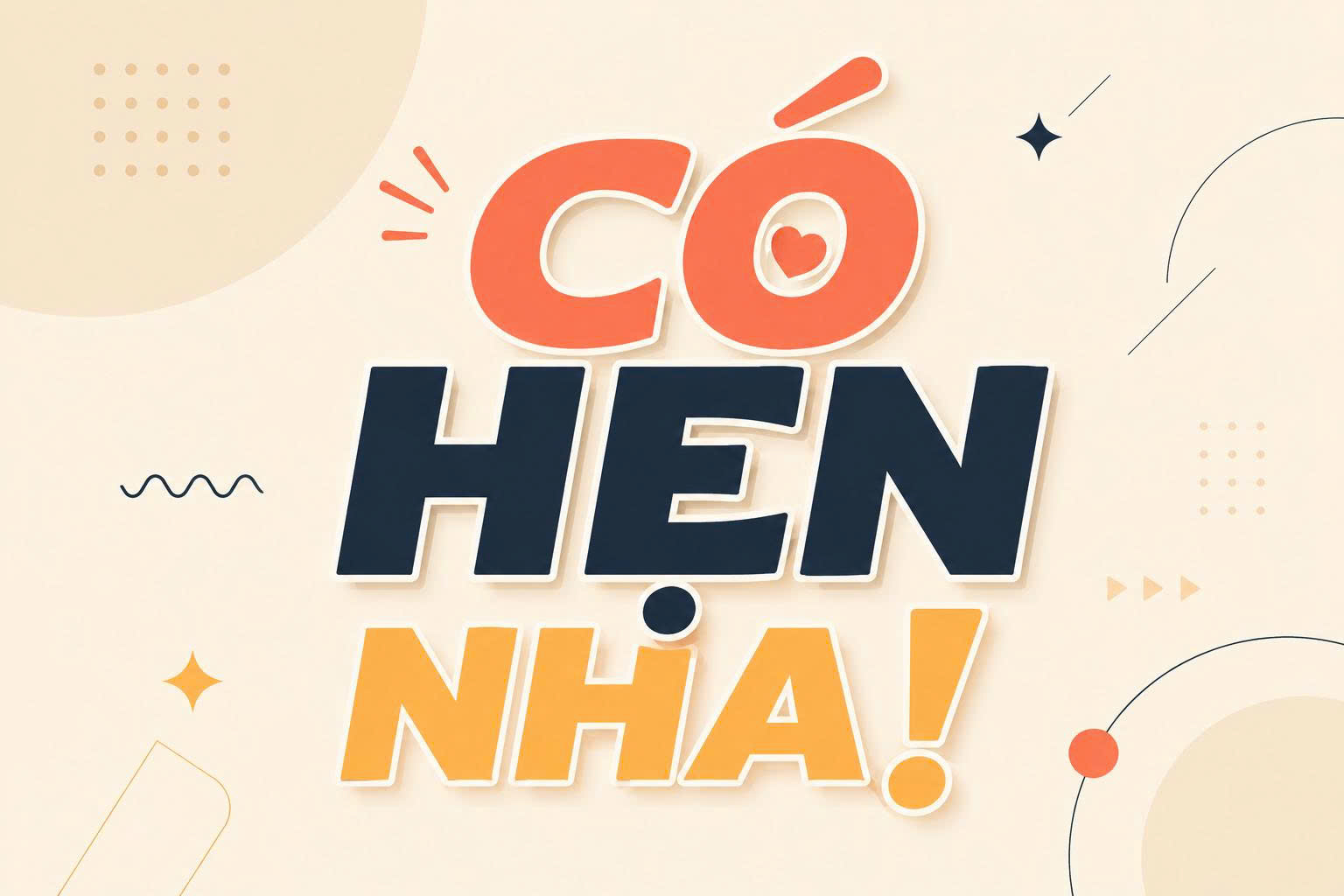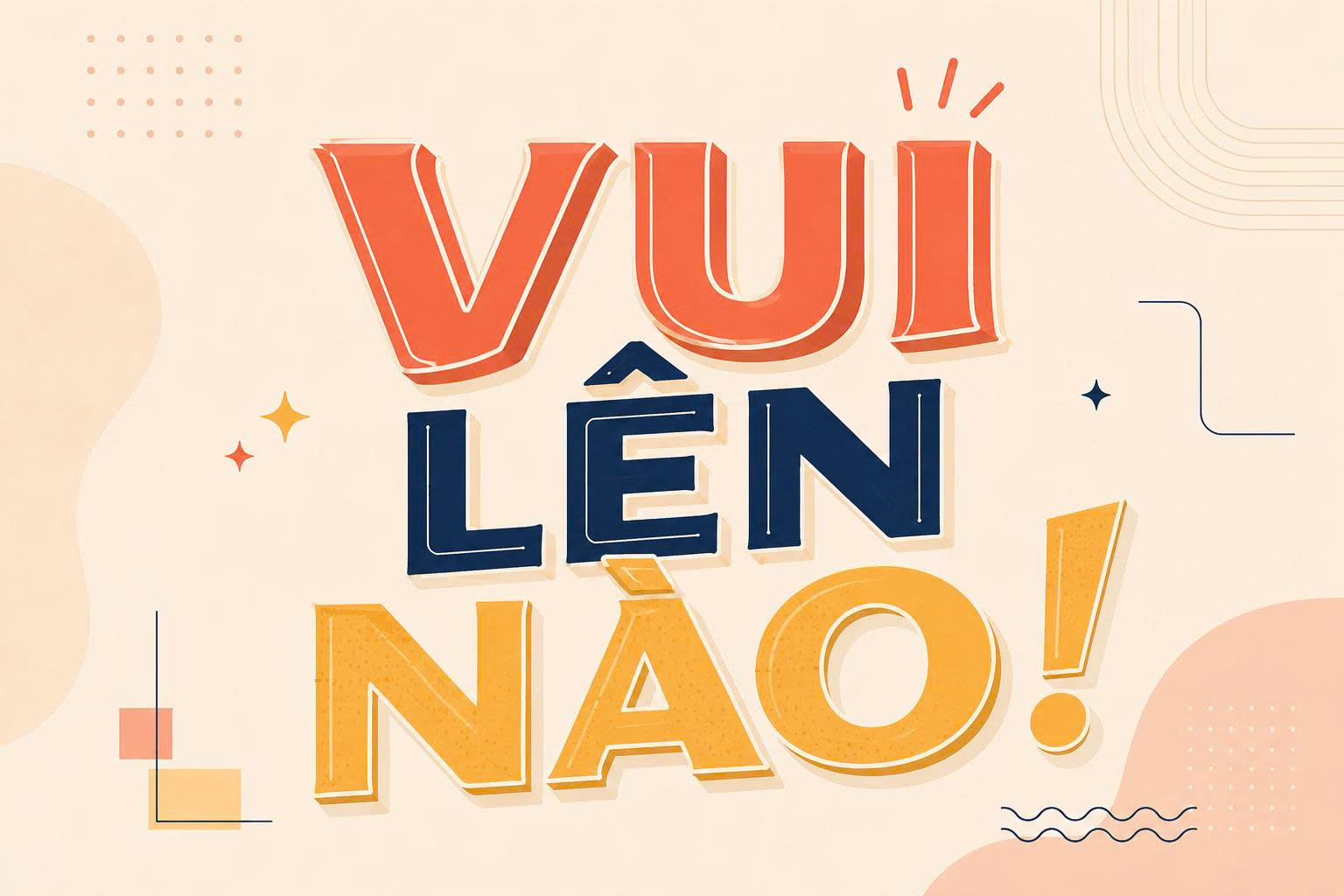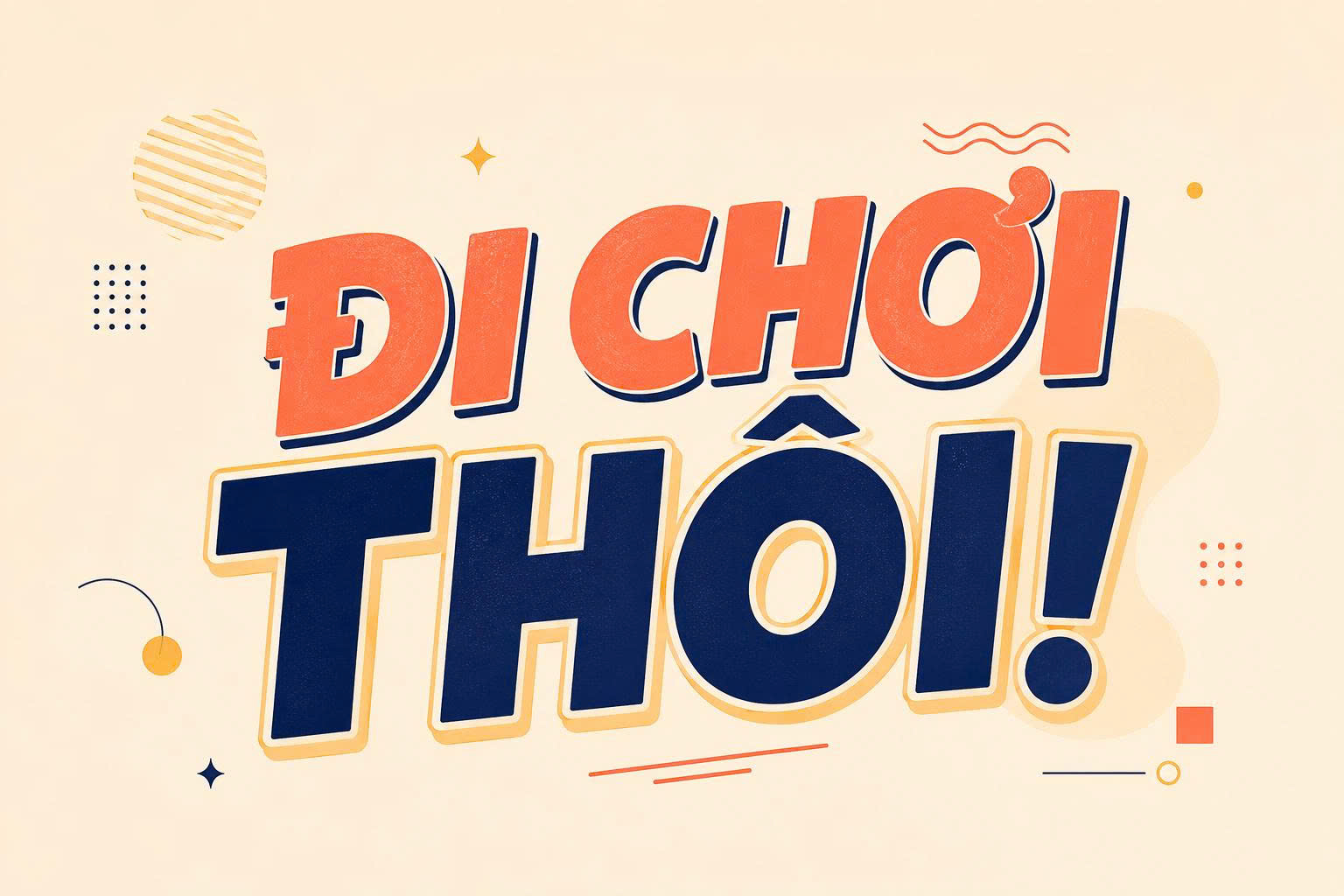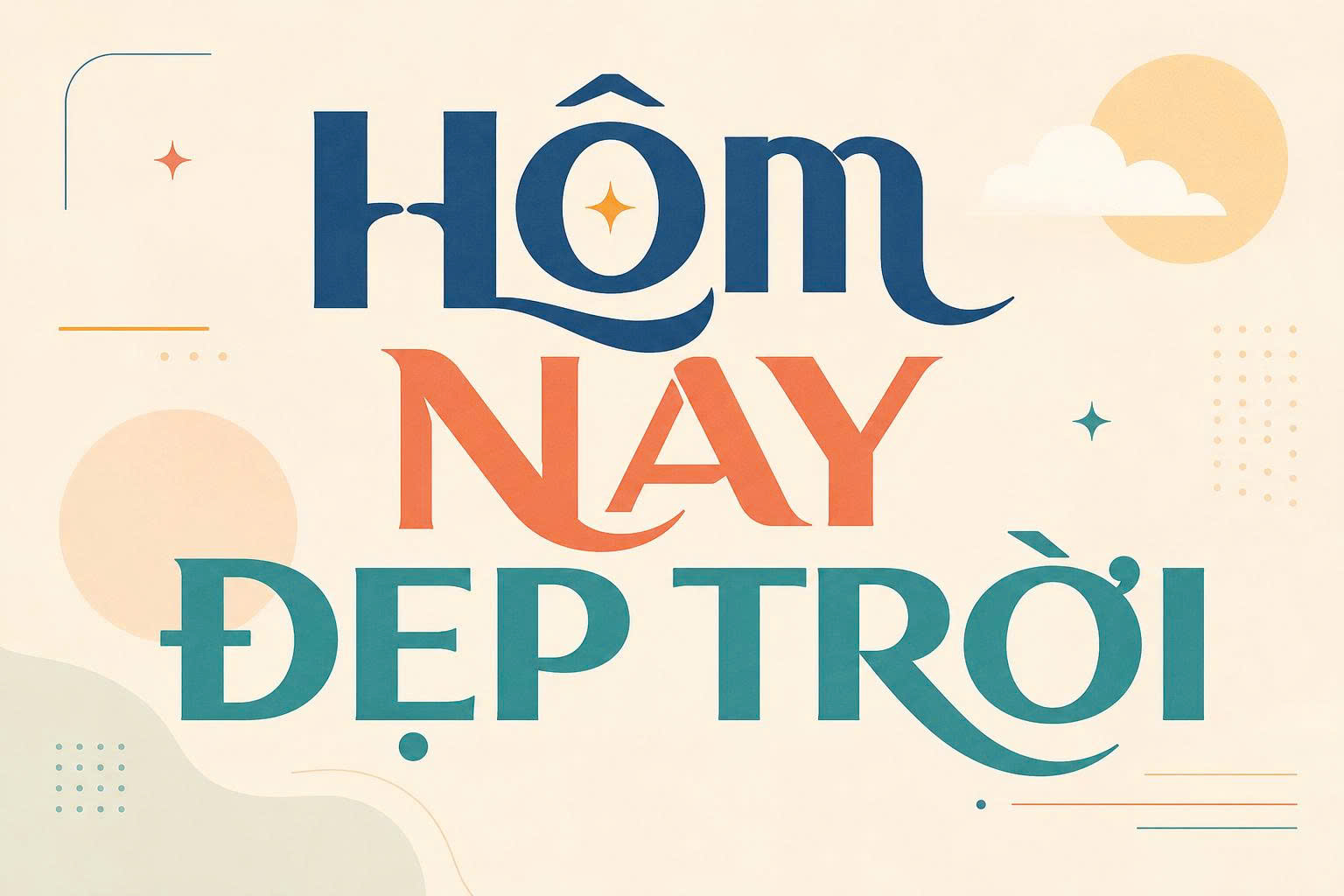
Font Chữ Đẹp PowerPoint – Gợi ý font trình chiếu đẹp, chuyên nghiệp | Doozypack.vn
Font chữ đẹp PowerPoint là yếu tố then chốt giúp bài thuyết trình của bạn trở nên chuyên nghiệp, lôi cuốn và truyền tải thông điệp hiệu quả hơn đến khán giả. Một bộ font ppt đẹp không chỉ dừng lại ở tính thẩm mỹ mà còn phải đảm bảo độ dễ đọc trên màn hình lớn cũng như khi in ấn tài liệu đính kèm. Doozypack.vn chia sẻ link tải font chữ Powerpoint đẹp trọn bộ đã được Việt hóa hoàn toàn, giúp bạn tự tin thiết kế slide mà không lo lỗi dấu hay sai lệch bố cục Typography.
Tại sao việc chọn font chữ đẹp cho PowerPoint lại quan trọng?
Trong thiết kế slide, phông chữ đóng vai trò là “giọng nói” thị giác của người thuyết trình. Việc lựa chọn đúng font chữ thuyết trình đẹp mang lại nhiều lợi ích thực tế:
• Tăng khả năng tập trung: Những phông chữ có cấu trúc rõ ràng giúp khán giả dễ dàng theo dõi nội dung ngay cả khi ngồi ở khoảng cách xa màn hình chiếu.
• Xây dựng sự uy tín: Sử dụng các dòng font hiện đại, đồng bộ giúp bài thuyết trình toát lên sự chuẩn bị bài bản và chuyên nghiệp của người thực hiện.
• Kết nối cảm xúc: Mỗi nhóm font (mạnh mẽ, thanh lịch hay vui nhộn) đều tạo ra một bầu không khí riêng, phù hợp với từng chủ đề thuyết trình từ kinh doanh đến nghệ thuật.
Mẫu chữ đẹp cho PowerPoint
Phân loại các font chữ PPT đẹp theo mục đích sử dụng
Để chọn được các font chữ ppt đẹp, bạn cần căn cứ vào nội dung và đối tượng người xem. Dưới đây là 3 nhóm font phổ biến nhất tại Doozypack.vn:
Nhóm font Sans-serif (Không chân) hiện đại
Đây là nhóm font đẹp cho PowerPoint được khuyên dùng nhiều nhất. Với các đường nét tối giản, không có gạch chân, dòng Sans-serif hiển thị cực kỳ sắc nét trên các thiết bị kỹ thuật số. Những cái tên kinh điển bao gồm: Montserrat, Roboto, Open Sans hoặc Be Vietnam Pro.
Font trình chiếu chuyên nghiệp
Nhóm font Serif (Có chân) trang trọng
Phù hợp cho các bài thuyết trình mang tính học thuật, lịch sử hoặc các thương hiệu cao cấp. Font Serif tạo cảm giác truyền thống, uy tín và vững chãi. Bạn có thể cân nhắc các bộ font như: Playfair Display, Crimson Text hoặc Times New Roman (bản cải tiến).
Nhóm font Display và Script tạo điểm nhấn
Nhóm này chỉ nên dùng cho tiêu đề chính hoặc các câu Quote ngắn để tạo sự phá cách. Những nét chữ mập mạp của dòng Display hay nét uốn lượn của Script giúp slide của bạn có “gu” nghệ thuật hơn hẳn.
Nhóm Font Đặc điểm thị giác Ứng dụng tốt nhất trên slide
Sans-serif Sạch sẽ, hiện đại, dễ đọc Dùng cho nội dung chi tiết (Body text) và tiêu đề phụ.
Serif Trang trọng, cổ điển Dùng cho bìa slide hoặc các chủ đề về tư vấn, luật pháp.
Display Nổi bật, thu hút Dùng làm tiêu đề lớn (Heading 1) hoặc các con số thống kê.
Lời khuyên từ chuyên gia thiết kế: Bạn nên kết hợp tối đa 2-3 font chữ trong một bài thuyết trình. Một font Sans-serif cho nội dung và một font Serif hoặc Display cho tiêu đề là công thức “vàng” để slide luôn hài hòa.
Thiết kế slide với kiểu chữ đẹp
• Kiểm soát độ tương phản: Luôn chọn màu chữ tương phản mạnh với màu nền slide (ví dụ chữ trắng trên nền tối hoặc chữ đen trên nền sáng) để tối ưu độ dễ đọc cho khán giả ngồi xa.